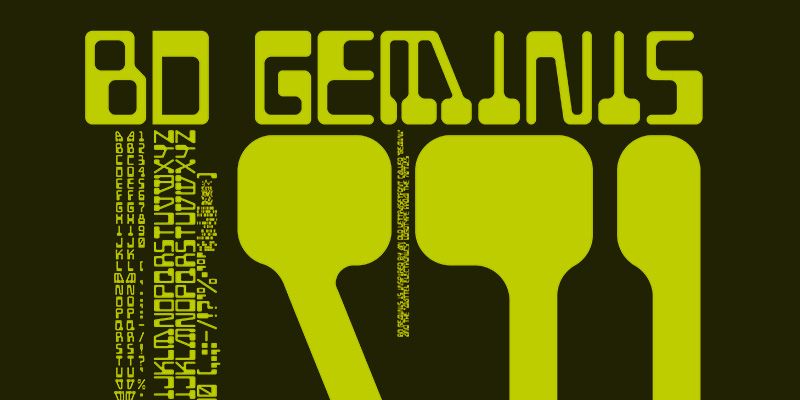
BD Geminis est une police informatique rétro numérique conçue par H1 en 2003.
Le studio de design graphique suisse « Büro Destruct » a été fondé en 1994 à Berne par « HGB Fideljus » Berger et Lorenz « Lopetz » Gianfreda. En 1995, Marc « MB » Brunner et Heinz « H1 » Reber ont rejoint le groupe. Au cours des années suivantes, Büro Destruct s’est développé pour devenir un studio de design pluridisciplinaire mondialement reconnu. Depuis 1995, Büro Destruct publie ses polices sur sa fonderie typographique « Typedifferent.com ». Comme ce nom l’indique, les polices de Büro Destruct ont souvent des caractéristiques de lettrage qui les rendent uniques. On les retrouve sur de nombreuses pochettes de disques, dans des magazines, des films et des émissions télévisées, sur des imprimés de mode ou encore des sites web.